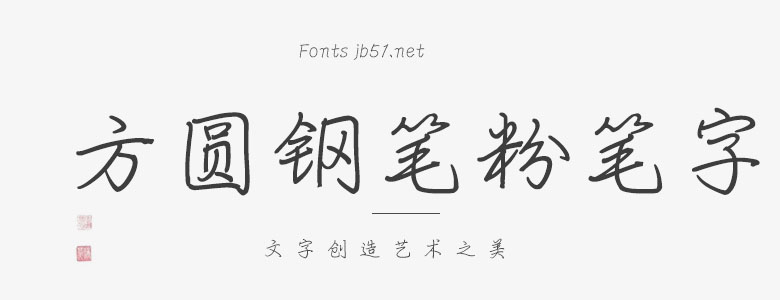
方圓鋼筆粉筆字是一款非常實(shí)用的中文粉筆字體,該字體線條非常纖細(xì),但字形飄逸大方得體,整體風(fēng)格非常的出色,可用于藝術(shù)設(shè)計(jì)、包裝印刷、簽名設(shè)計(jì)、圖形設(shè)計(jì)等領(lǐng)域,有喜歡的朋友可免費(fèi)下載收藏。